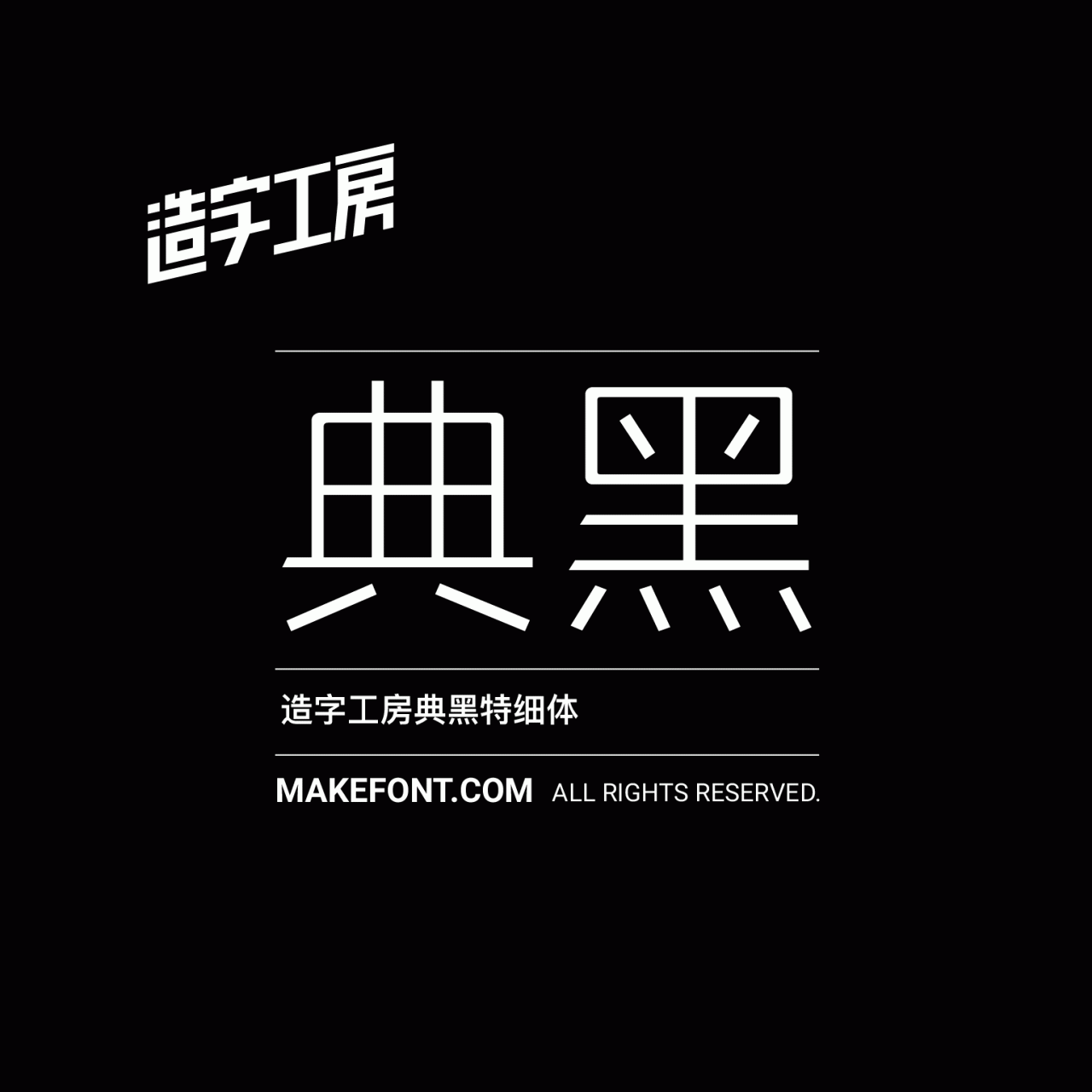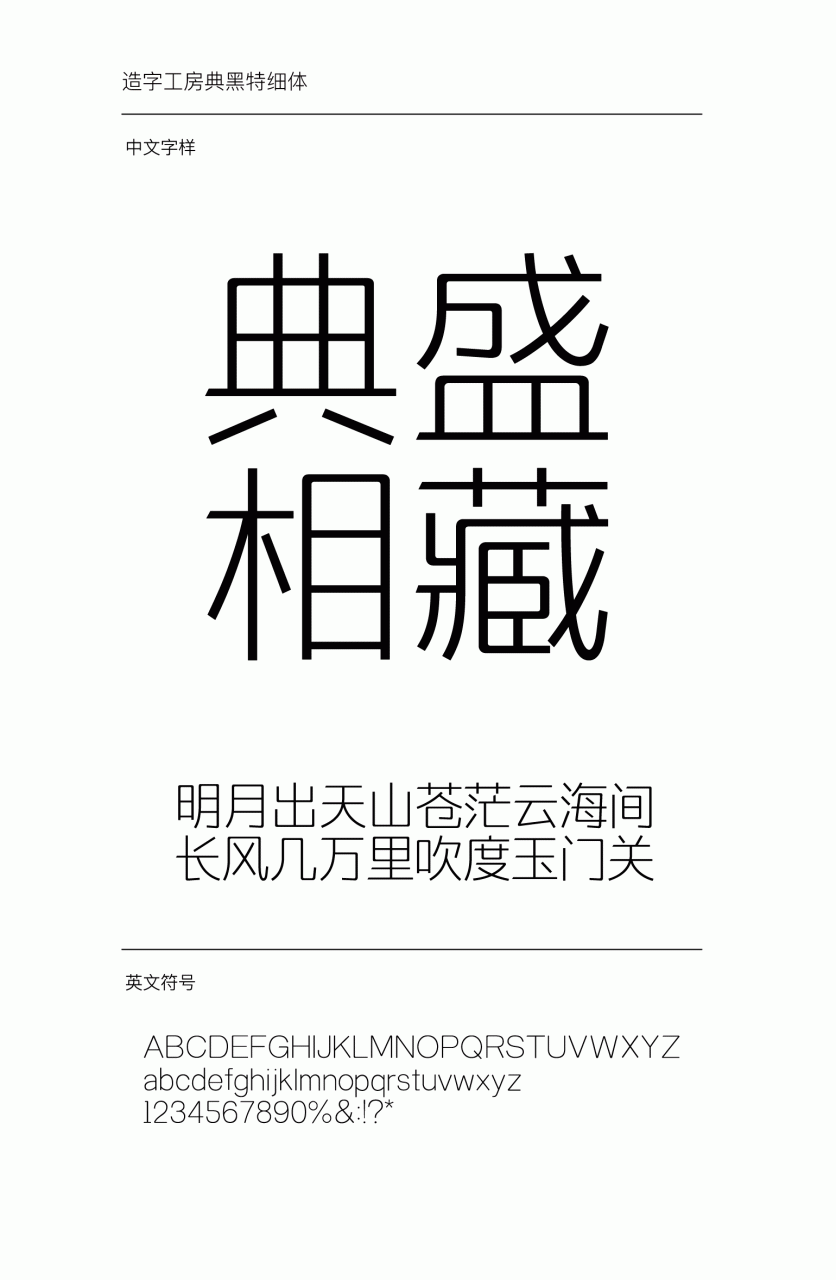
造字工房典黑特细体设计说明
造字工房典黑体,字形方正严谨、笔画简洁有力、中宫清晰,在黑体字形基础之上巧妙创新,使其字形笔画柔和而不失刚毅,风格鲜明且极具易读性。适用于文字标题、广告设计乃至正文等视觉环境,有着极强的应用空间。 本字体为简体字库,采用OpenType/CID格式,Adobe-GB1-5编码。基于中华人民共和国GB2312-80字符集标准,另按需添加101个汉字。共收容字数6864CJK汉字,ASCII常用字符100个。